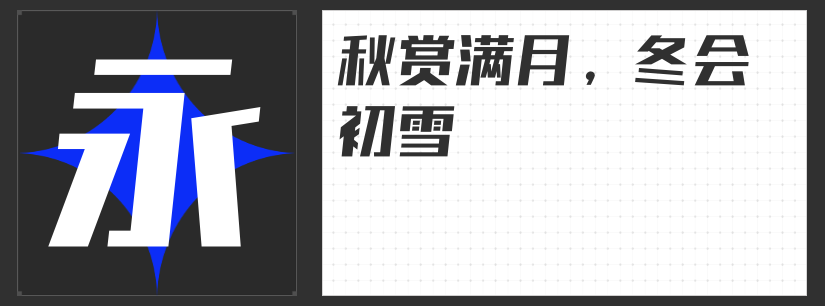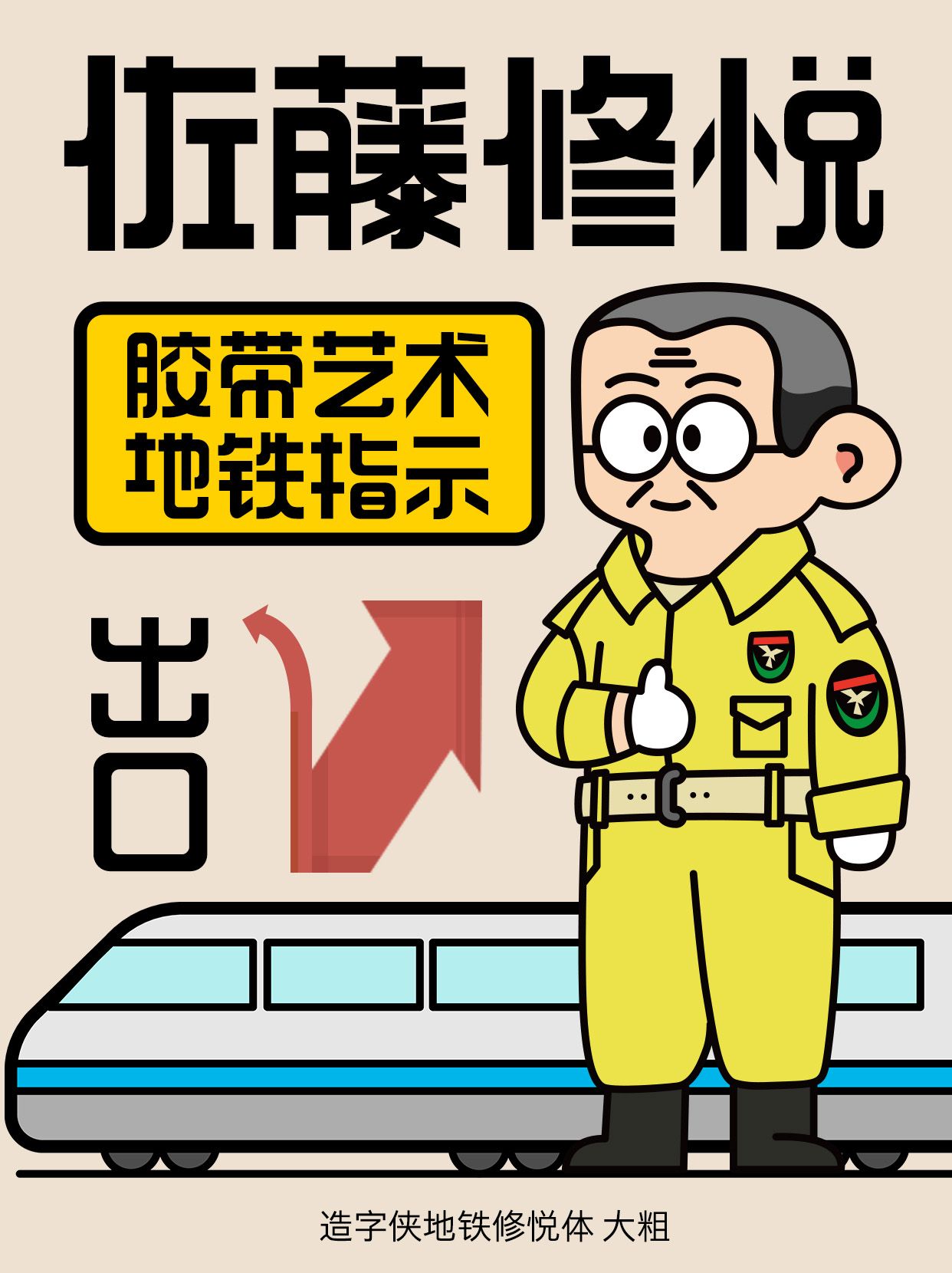
让公众号文章更出彩:四款精选字体,让内容跃然屏上
在公众号运营的浩瀚海洋中,字体不仅是文字的载体,更是情感与风格的传递者。今天,就为大家推荐四款专为公众号量身打造的字体,它们各具特色,定能让你的内容更加引人入胜。
是一款以胶带为灵感创作的字体。造字侠地铁修悦体 大粗以其低重心、高艺术感的设计,成为版头设计的不二之选。它仿佛为文字穿上了时尚的盔甲,既稳固又充满创意,瞬间提升图文的视觉冲击力,让读者一眼难忘。
2.高手兵克侠客体
当古风遇上侠义,高手兵克侠客体应运而生。这款字体笔锋凌厉,透露出浓厚的武侠气息,非常适合用于公众号海报设计或重点板块的突出展示。它能让你的内容仿佛穿越千年,与读者共赴一场江湖之约。
追求简洁与现代的你,怎能错过高手庆科帅黑体 大黑?这款字体线条清晰,结构稳健,散发着强烈的现代感,非常适合用作公众号文章的标题。它能让你的标题瞬间脱颖而出,吸引读者的眼球,引领阅读潮流。
最后,让我们来感受造字侠灵霄简繁 传神的独特魅力。每一笔一划都透露出书写者的情感与温度。它潇洒而不失细腻,非常适合用于公众号中的情感类文章,让文字与读者之间建立起更加亲密的联系。
四款字体,四种风格,总有一款能触动你的心弦。在公众号运营的路上,不妨尝试这些新宠儿,让你的内容更加丰富多彩,吸引更多读者的关注与喜爱。